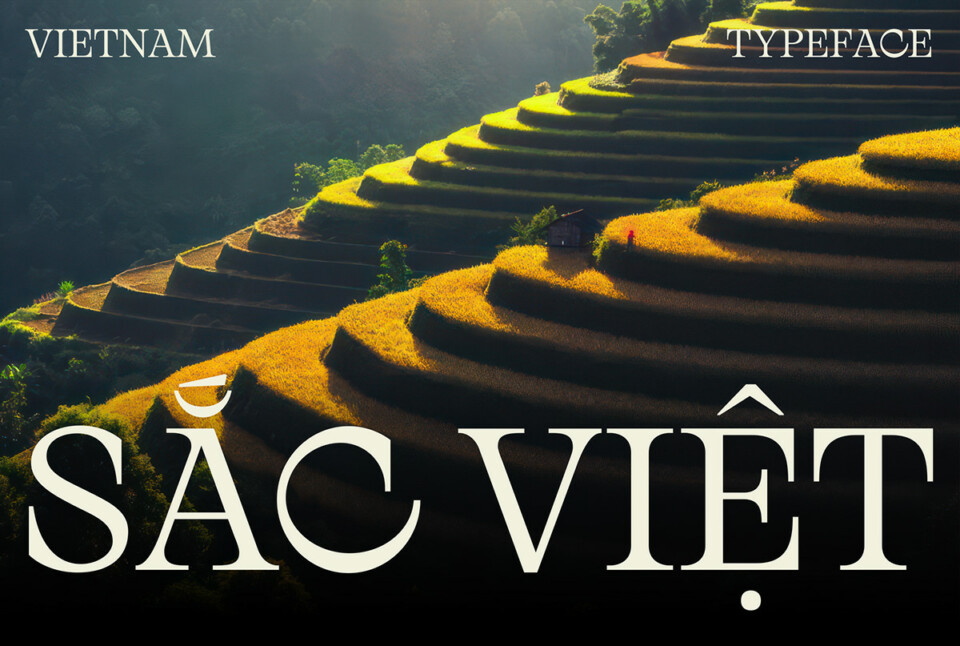
Giới thiệu về Font Sắc Việt typefaces ( Free to use )
Trong kỷ nguyên số hóa giáo dục hiện nay, việc lựa chọn một Font Chữ phù hợp đóng vai trò quan trọng trong việc truyền tải kiến thức. Bộ sưu tập Font Sắc Việt typefaces ( Free to use ) được thiết kế nhằm mang đến giải pháp Typography tối ưu cho người dùng Việt Nam. Với tính năng miễn phí hoàn toàn, bộ font này giúp học sinh và giáo viên dễ dàng tiếp cận các kiểu chữ đẹp mắt mà không lo ngại về vấn đề bản quyền. Đặc biệt, các ký tự tiếng Việt được chăm chút kỹ lưỡng, đảm bảo tính thẩm mỹ và sự đồng nhất trong mọi văn bản học thuật.
Ưu điểm nổi bật của Font Sắc Việt typefaces ( Free to use )
Thiết kế tối ưu cho giáo dục
Bộ Font Sắc Việt typefaces ( Free to use ) sở hữu đường nét rõ ràng, dễ đọc, rất phù hợp để làm tài liệu giảng dạy hoặc trình chiếu bài giảng. Sự đa dạng trong các biến thể từ Bold đến Light giúp người dùng linh hoạt trong việc nhấn mạnh nội dung quan trọng. Những bộ font này không chỉ hỗ trợ hiển thị tốt trên màn hình máy tính mà còn sắc nét khi in ấn ra giấy, giúp bảo vệ thị lực cho học sinh khi tiếp xúc với giáo trình trong thời gian dài.
Kết luận về bộ sưu tập font chữ
Việc sử dụng các bộ font Việt hóa chất lượng cao sẽ nâng tầm giá trị cho các sản phẩm sáng tạo của bạn. Hãy trải nghiệm ngay Font Miễn Phí, Font Việt Hóa, Font Sắc Việt typefaces ( Free to use ) để cảm nhận sự khác biệt trong từng nét chữ. Đây chính là công cụ hỗ trợ đắc lực cho cộng đồng học thuật trong hành trình tìm kiếm vẻ đẹp của con chữ Việt.